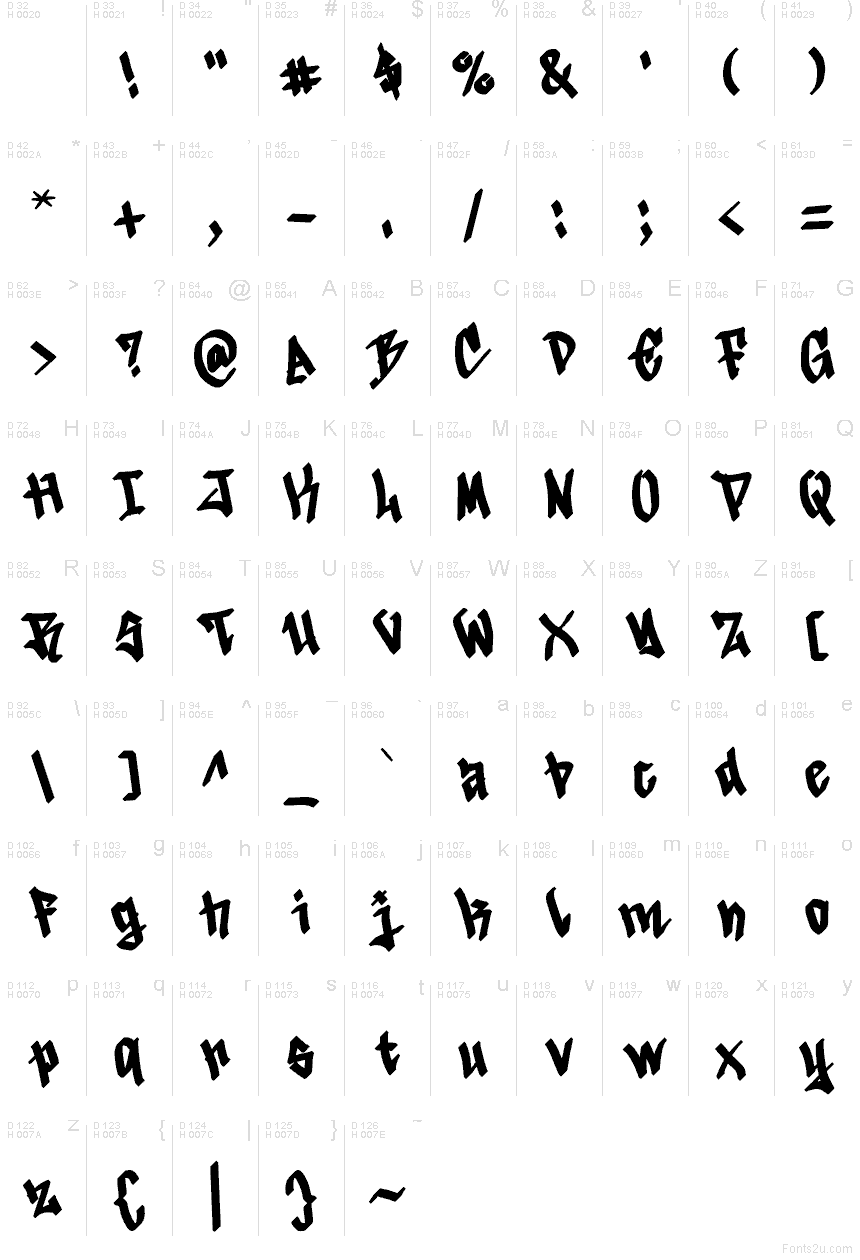
Quick Brick هو خط جرافيتي مجاني يتميز بضربات حادة تشبه الخطوط القوطية (Blackletter) وقطع زاوي صلب يمنح كل حرف شعوراً بالتجسيد، كأنه نقش على جدران الشوارع. تتداخل الأشكال معاً بشكل محكم، مع أطراف مدببة وحواف غير منتظمة تحافظ على الطابع الخشن والحرفي للتصميم، بعيداً عن أي صقل أو رسمية مفرطة.
يعتبر Quick Brick ممتازاً لعناوين الملصقات، وأغلفة الألبومات، وتصاميم أزياء الشارع، والخطوط المستوحاة من فن الوشم، ومنشورات الفعاليات، والشعارات التي تحتاج إلى لمسة حضرية جريئة. يجلب هذا الخط المجاني ما يكفي من الشخصية للعبارات القصيرة والاستخدامات العرضية، حيث يمكن لإيقاعه المتقطع وأشكاله المائلة أن تحمل التصميم بأكمله دون الحاجة إلى زخارف إضافية.